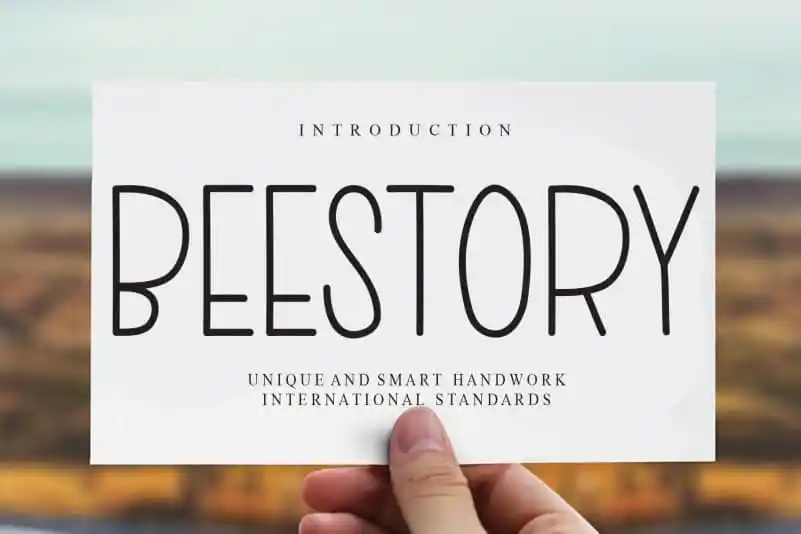
Beestory Display Font – Download Grátis
A fonte Beestory Display Font é perfeitamente adaptada para decorar ambientes e criar experiências memoráveis. Seu estilo único e detalhado permite que você personalize qualquer projeto, seja uma criação gráfica minimalista ou um design exuberante com bordas arredondadas e linhas finas suaves. Com a Beestory Display Font da designer creativeletter, cada letra ganha vida em suas obras, tornando-as verdadeiras obras de arte para seus projetos decorativos. Esta fonte é ideal tanto para cartazes de loja como para aplicação em sites, mantendo sua identidade visual inconfundível e destacada. Com uma paleta sofisticada que combina harmonicamente com estilos diversos, ela oferece flexibilidade para diferentes ambientes e contextos gráficos. Descubra o verdadeiro potencial da Beestory Display Font e revolucione a maneira como você visualiza e cria design decorativo.